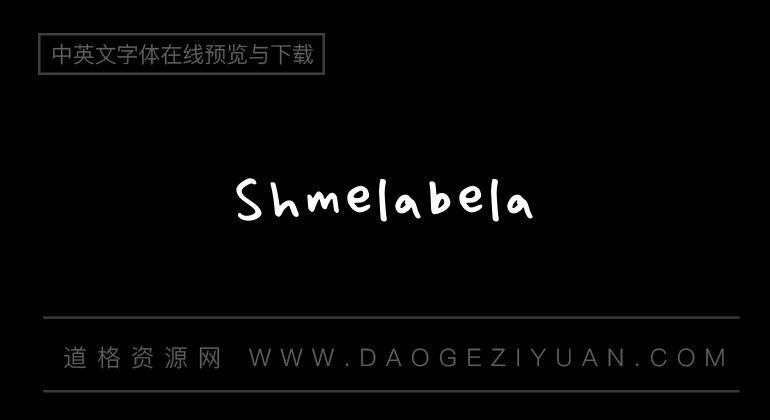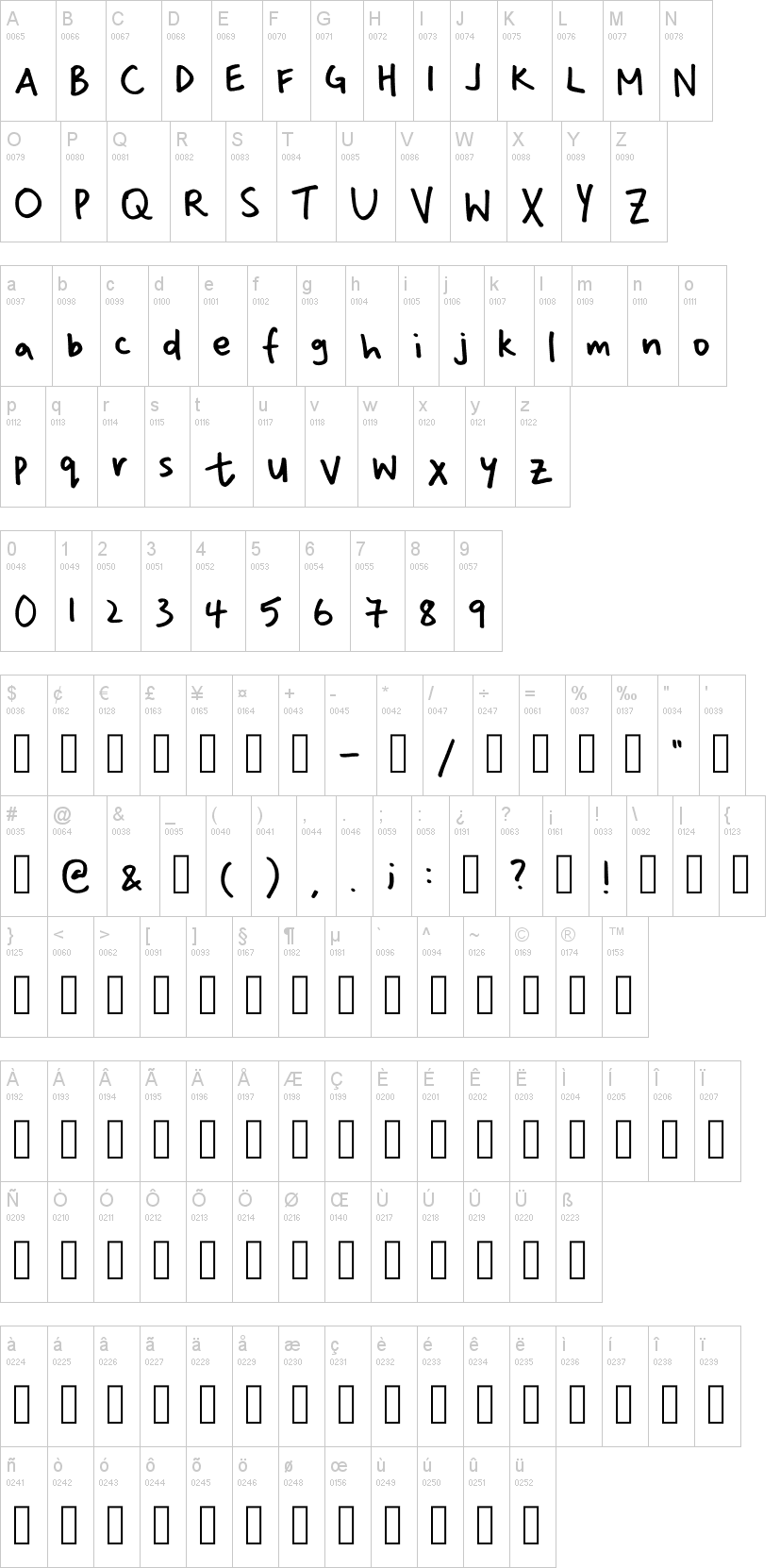
Shmelabela
Shmelabela 是一款来自俄罗斯的自由字体,由设计师Alexander Shmelkov设计。它是一种明快、活泼的手写字体,有着浓郁的欧洲风格,适合用于海报、标语、海报、包装、品牌标识等等。它具有温暖、时尚、活泼、明快的特点,可以让你的设计更加有趣。此外,Shmelabela 字体还支持多种语言,可以满足不同的需求。
Shmelabela是一款非常不错的手写艺术字体,具有很好的视觉感,适合于文化类的宣传设计、商业类品牌的广告和产品包装设计以及个性化文字排版等较多场景。
Shmelabela字符映射图